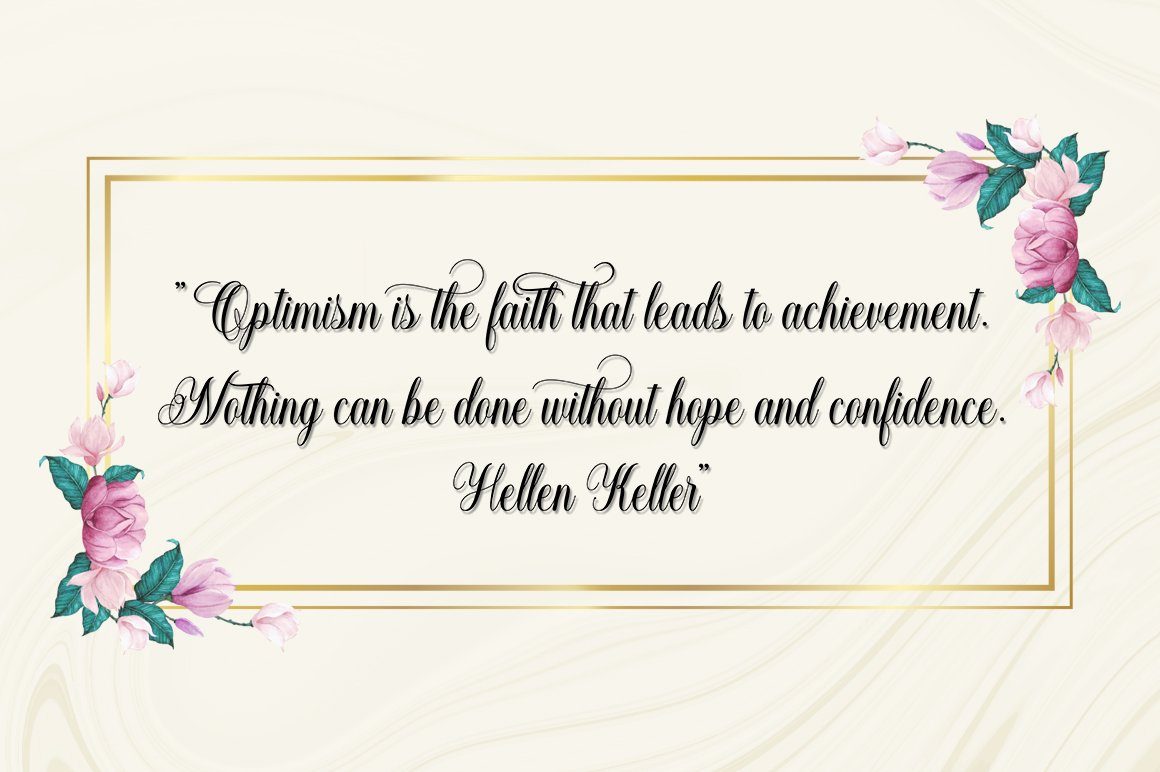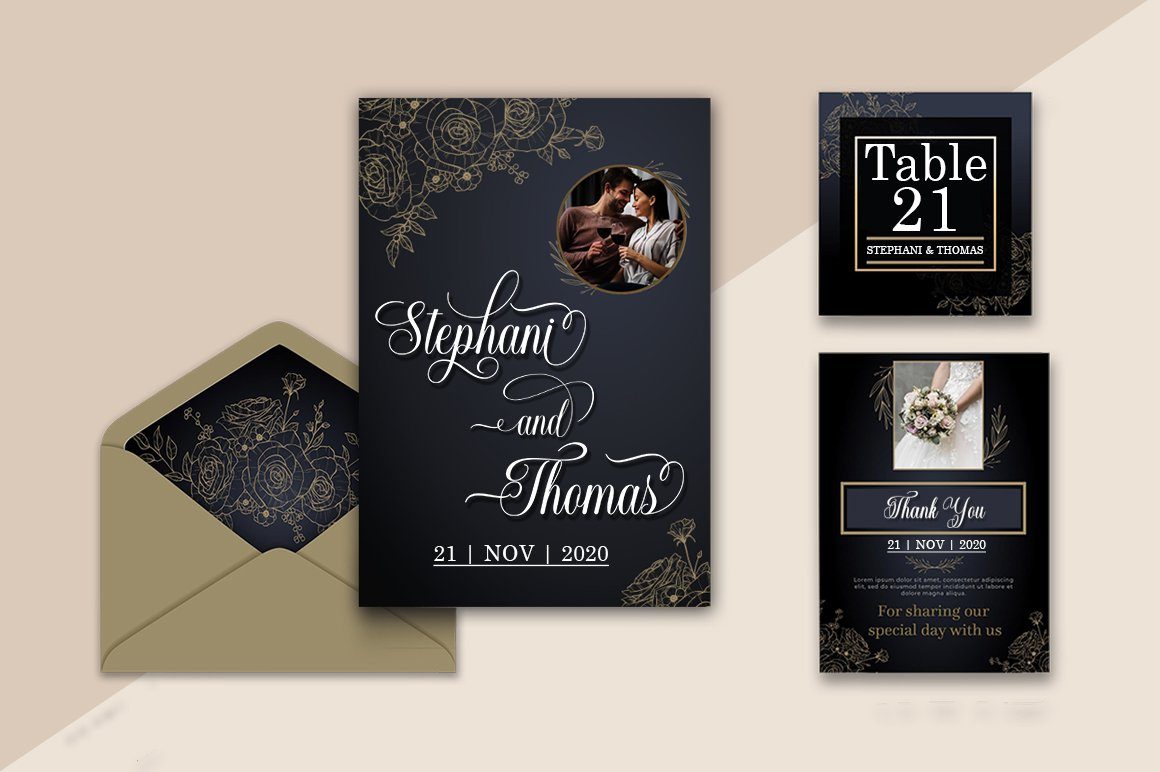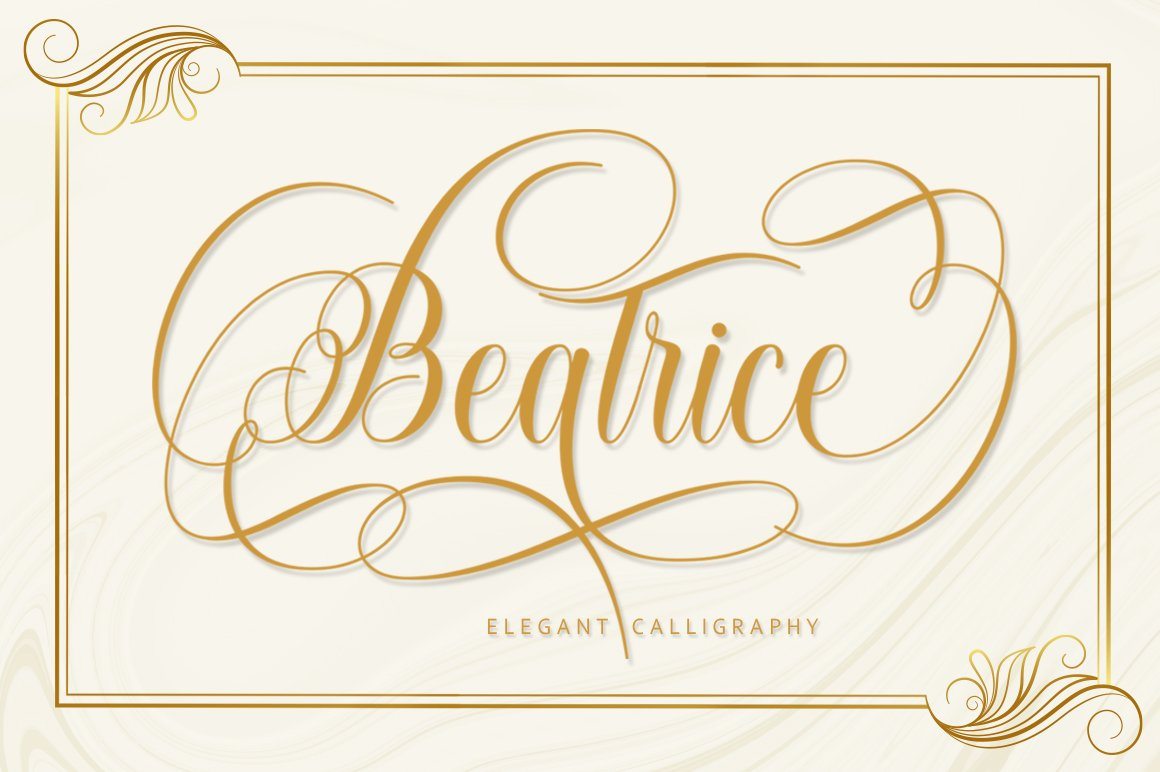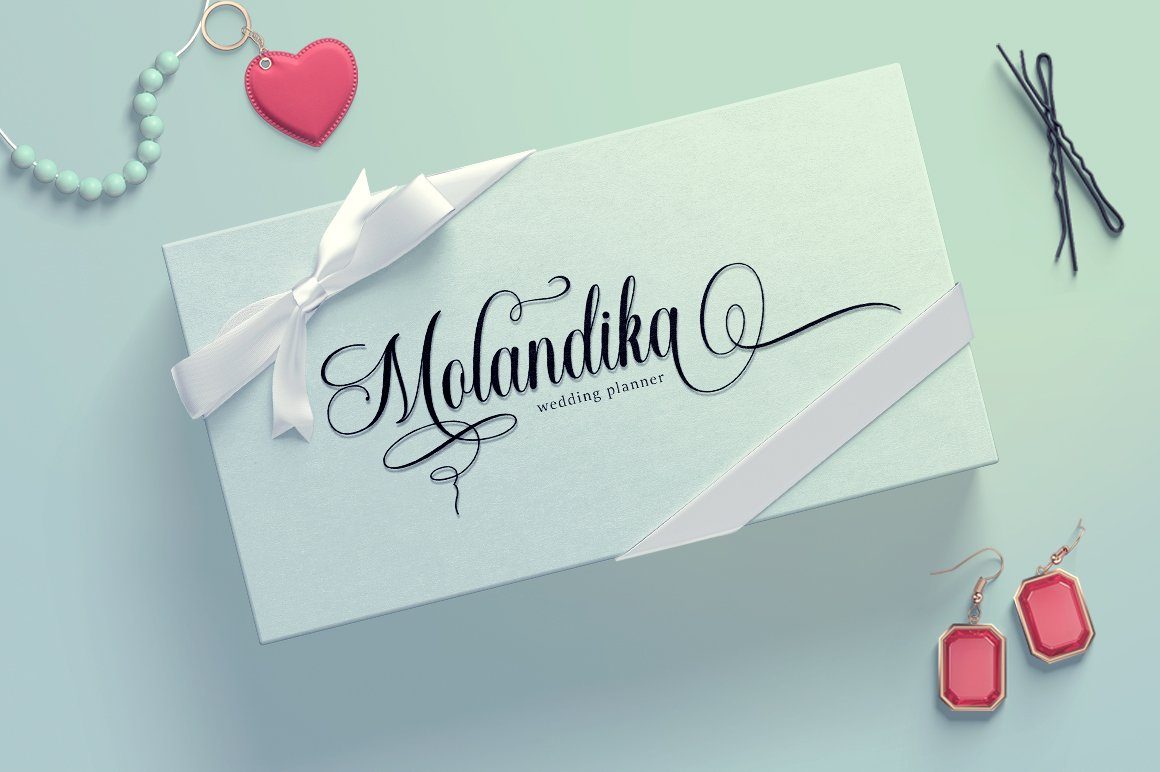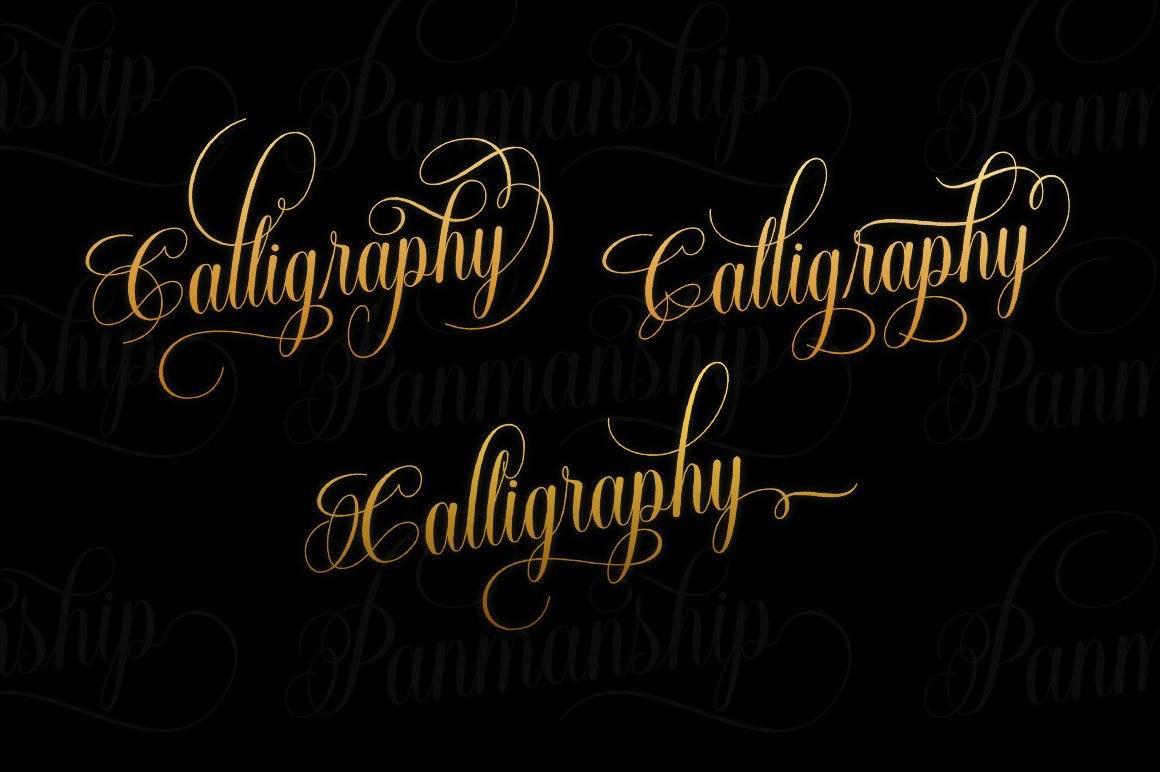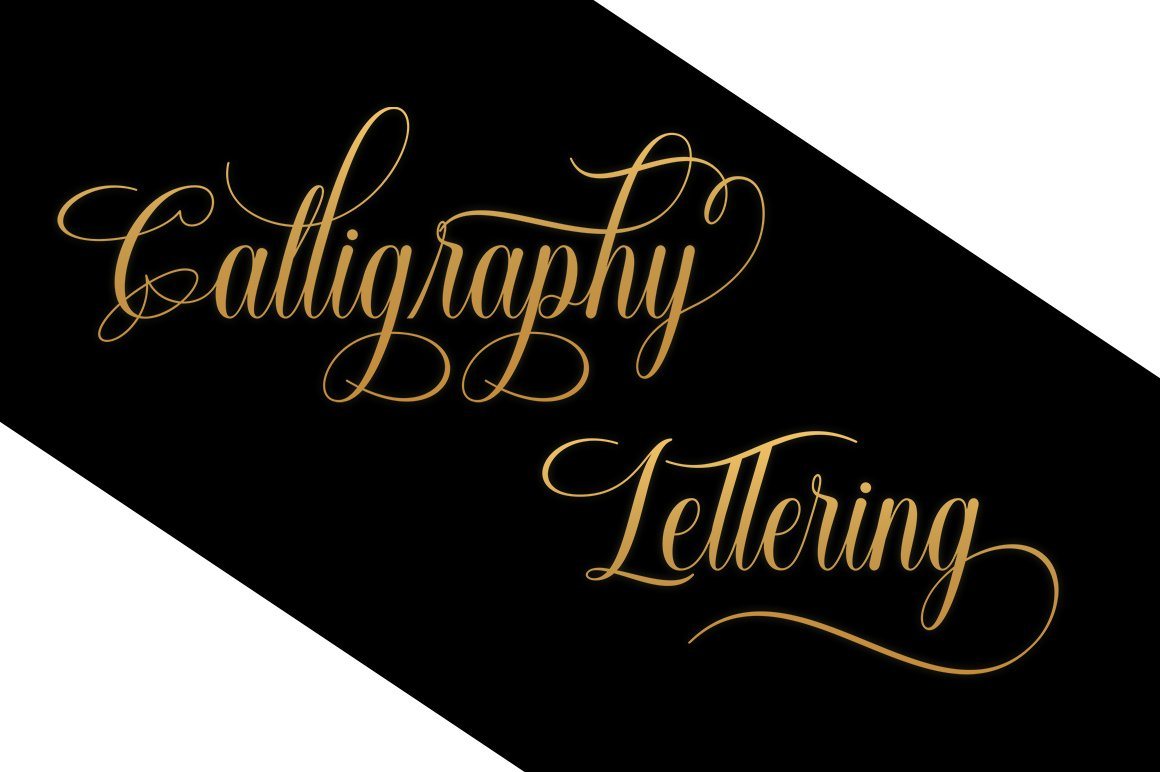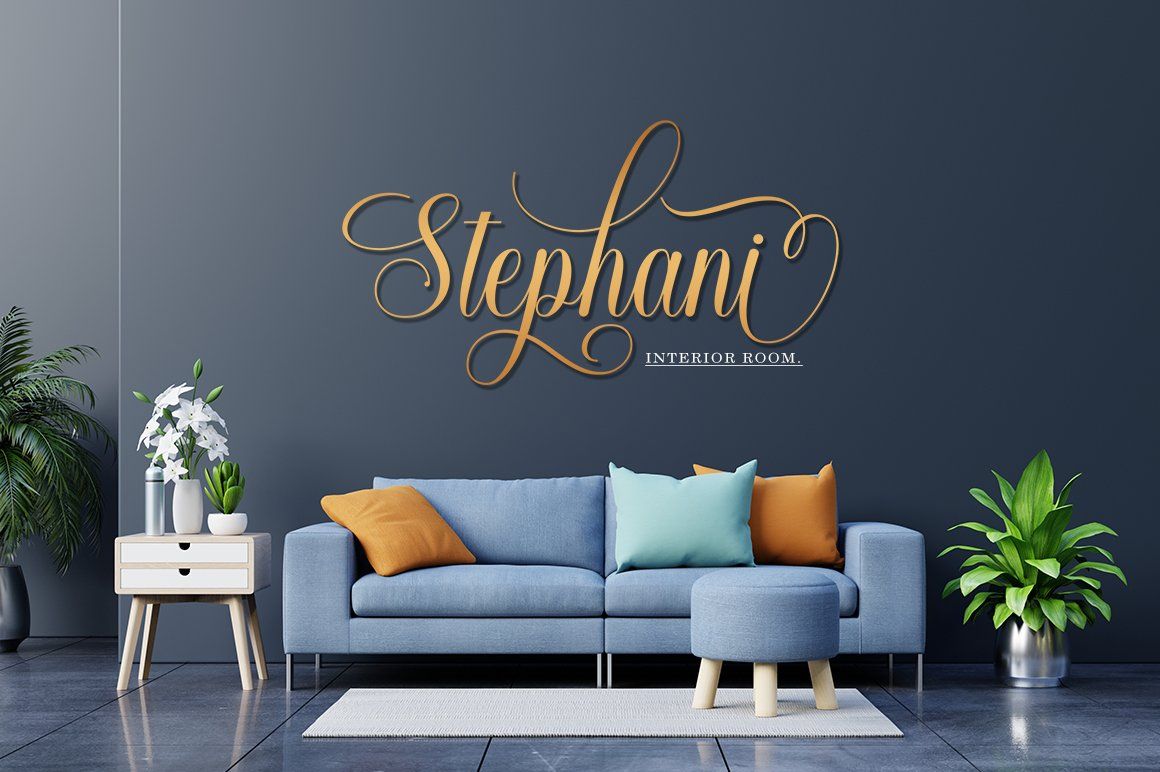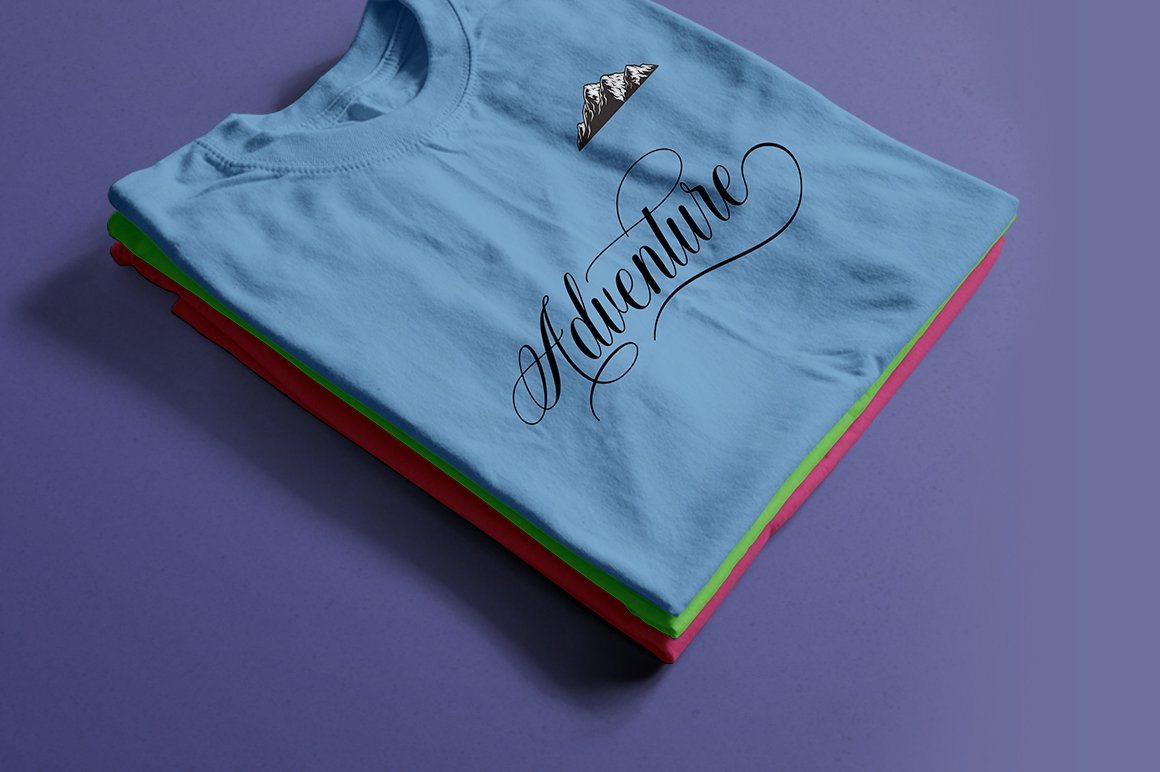
Beatrice
About Beatrice
Beatrice Script adalah font tulisan kaligrafi yang hadir dengan perubahan karakter yang sangat indah, semacam skrip dekoratif tembaga klasik dengan sentuhan modern, dirancang dengan detail tinggi untuk menghadirkan gaya yang elegan. Beatrice Script menarik karena memiliki jenis huruf yang lembut, bersih, feminin, sensual, glamor, sederhana dan sangat mudah dibaca, karena terdapat banyak sambungan huruf yang mewah. Saya juga menawarkan sejumlah alternatif gaya yang layak untuk beberapa huruf. Gaya klasik sangat cocok diterapkan dalam berbagai bentuk formal seperti undangan, label, menu restoran, logo, fashion, make up, alat tulis, novel, majalah, buku, kartu ucapan/nikah, kemasan, label atau segala jenis keperluan periklanan. . . Beatrice Script memiliki 1077+ mesin terbang dan 929 karakter alternatif, termasuk dukungan berbagai bahasa. Dengan fitur OpenType dengan gaya alternatif dan penjilidan yang elegan. Fitur OpenType tidak bekerja secara otomatis, tetapi Anda dapat mengaksesnya secara manual dan untuk hasil terbaik diperlukan kreativitas Anda dalam menggabungkan variasi Glyph ini.